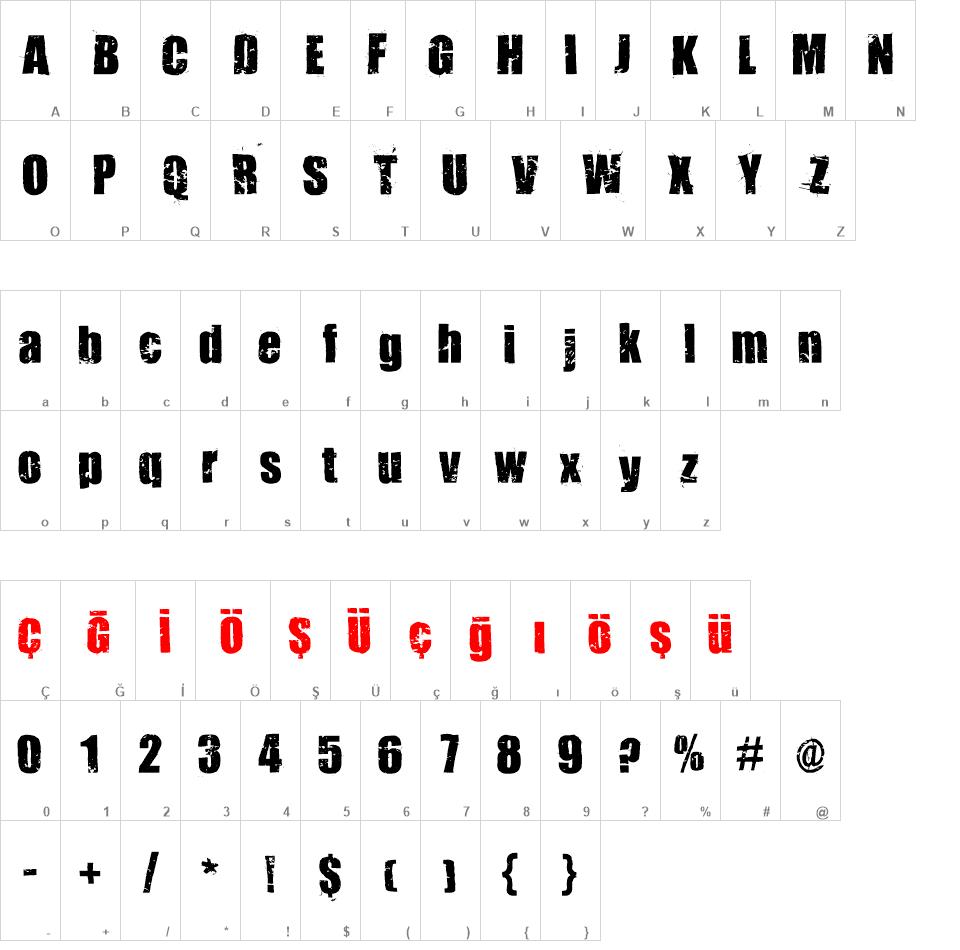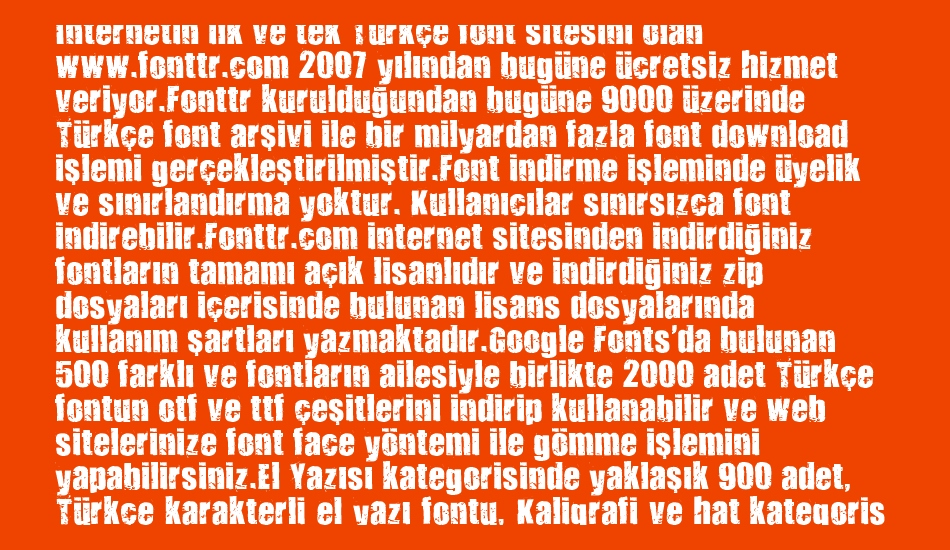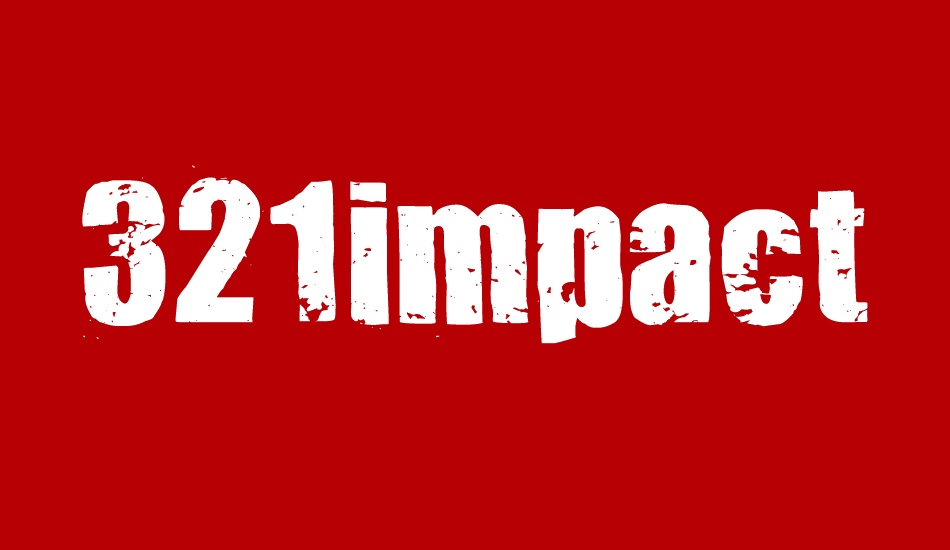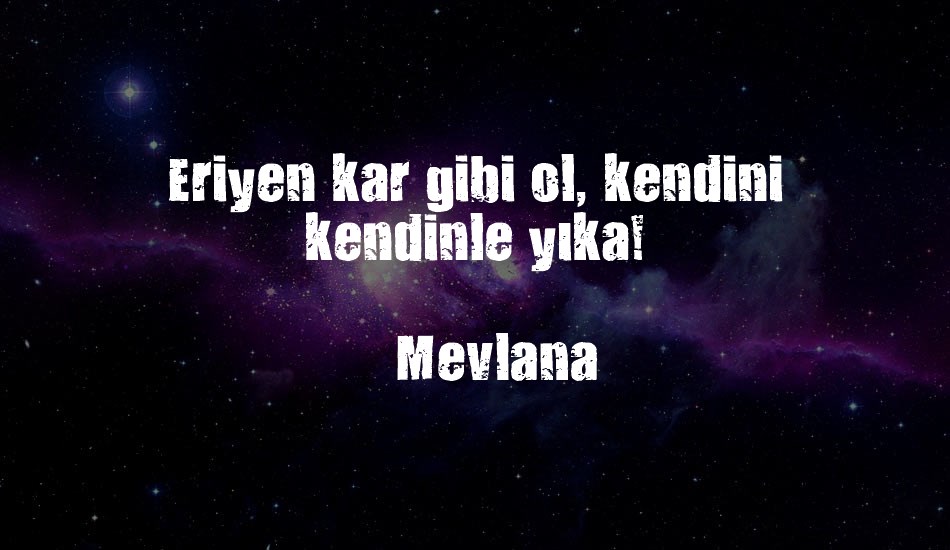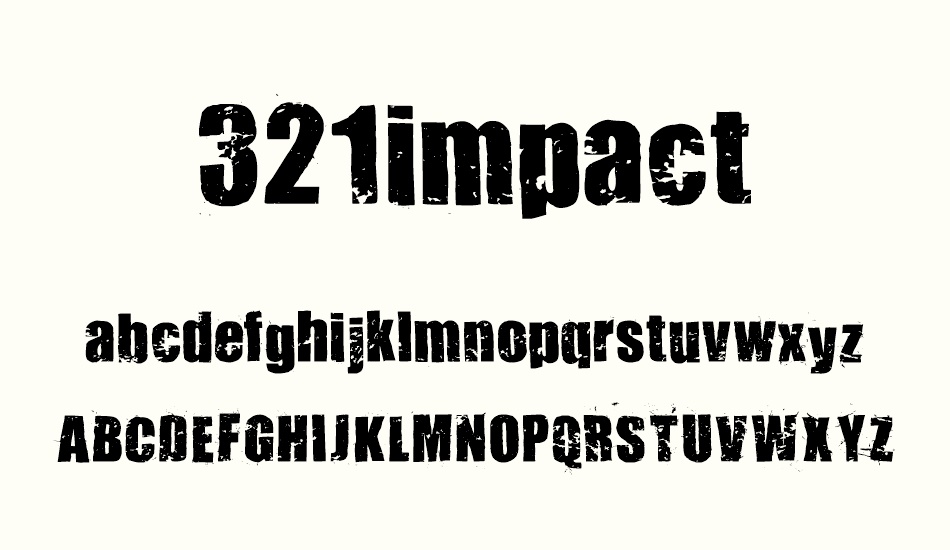
321 impact font
321 impact eskitme türkçe font, haber siteleri bannerlarında tehlikeli haber başlık karakteri olarak tercih edilmektedir. Türkçe karakterleri uyumludur. 321 impact indir.